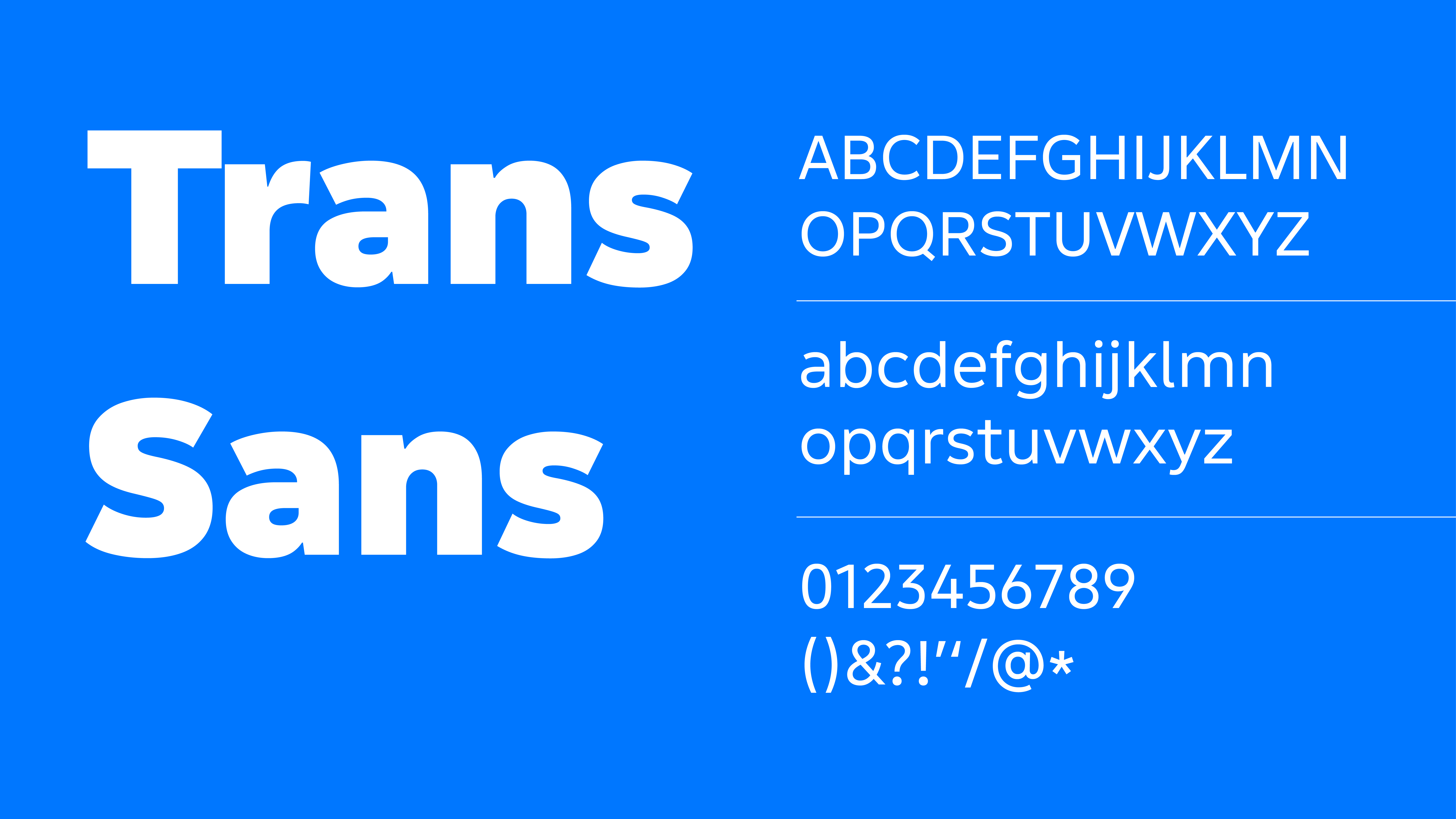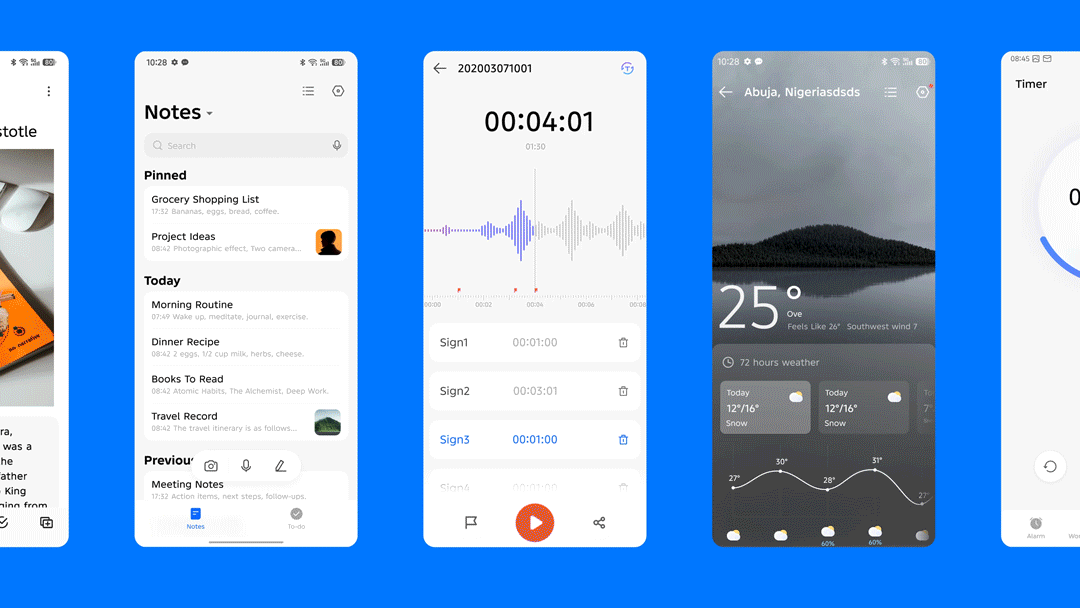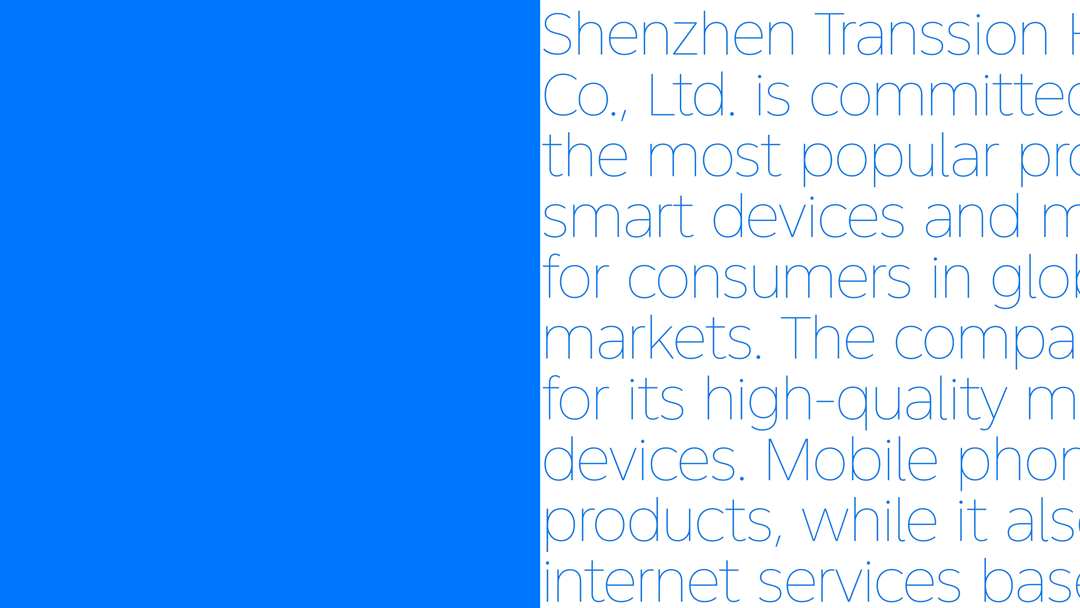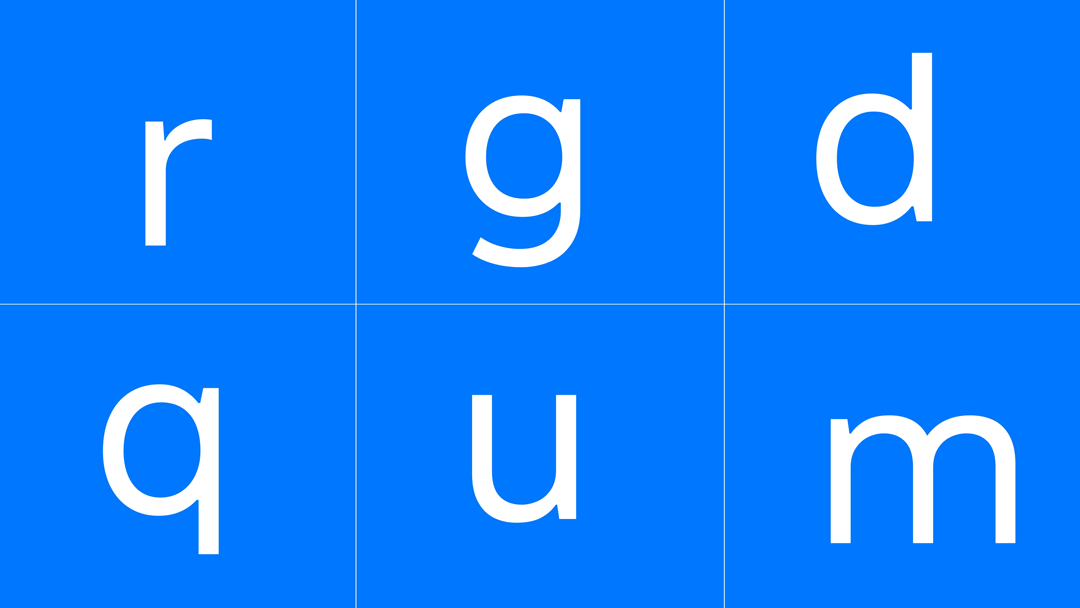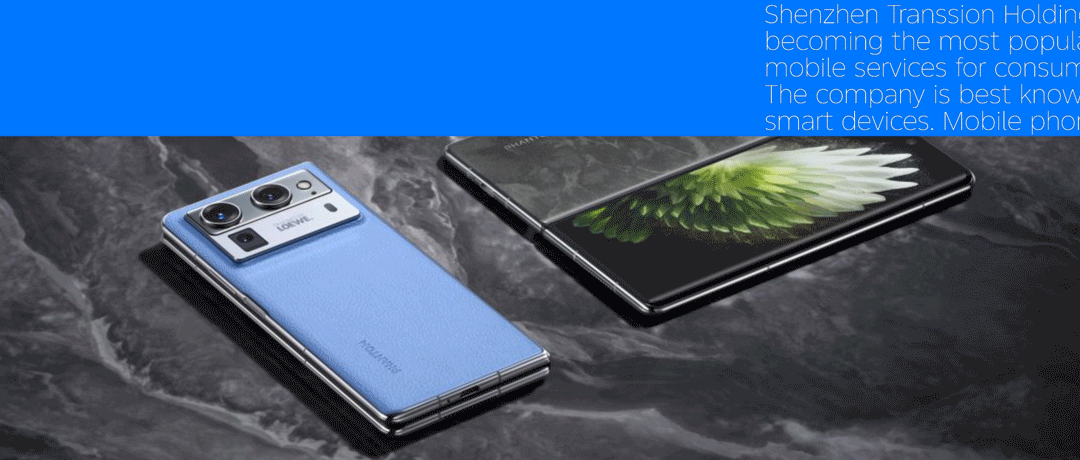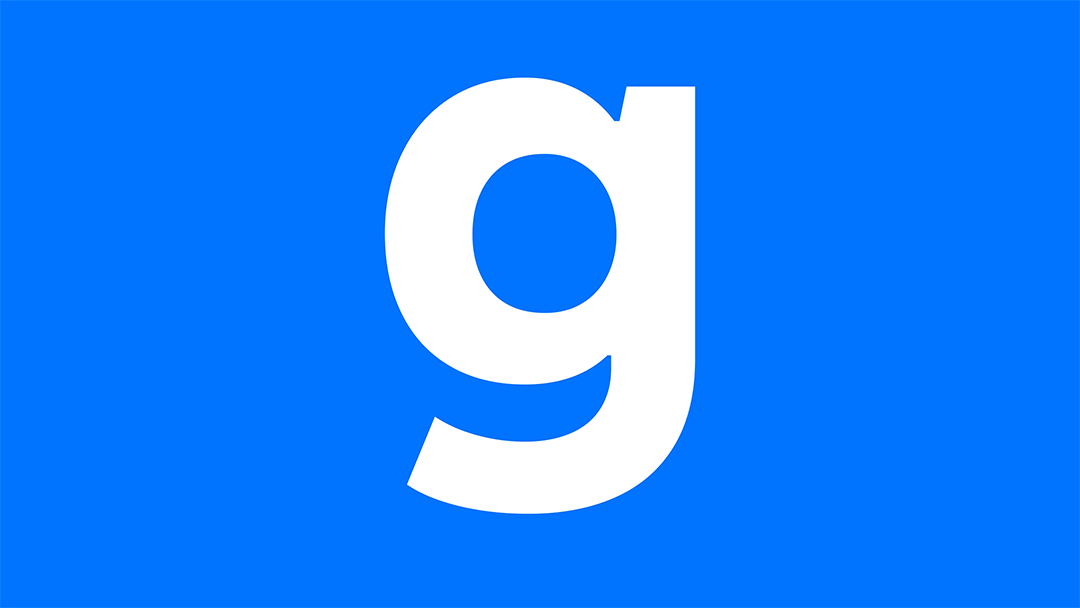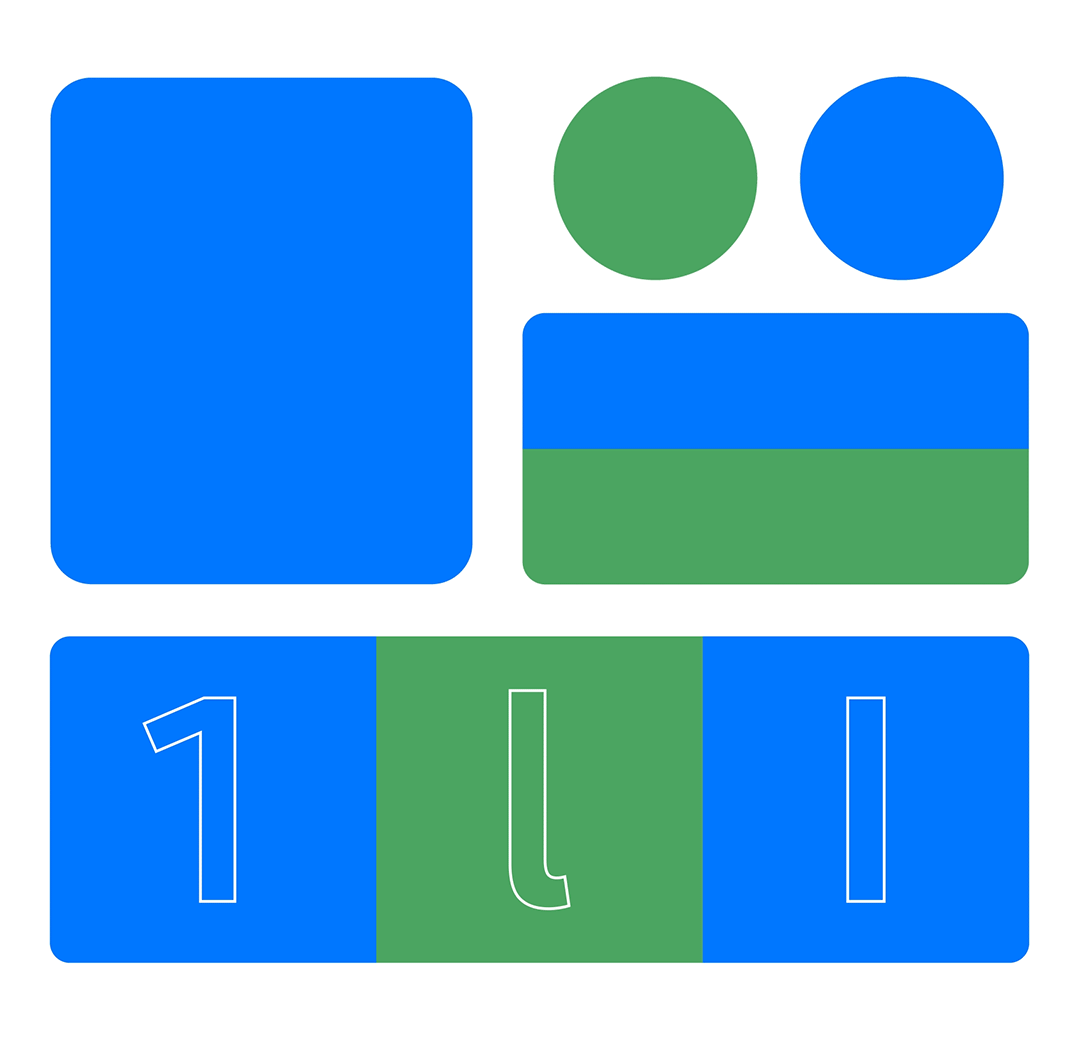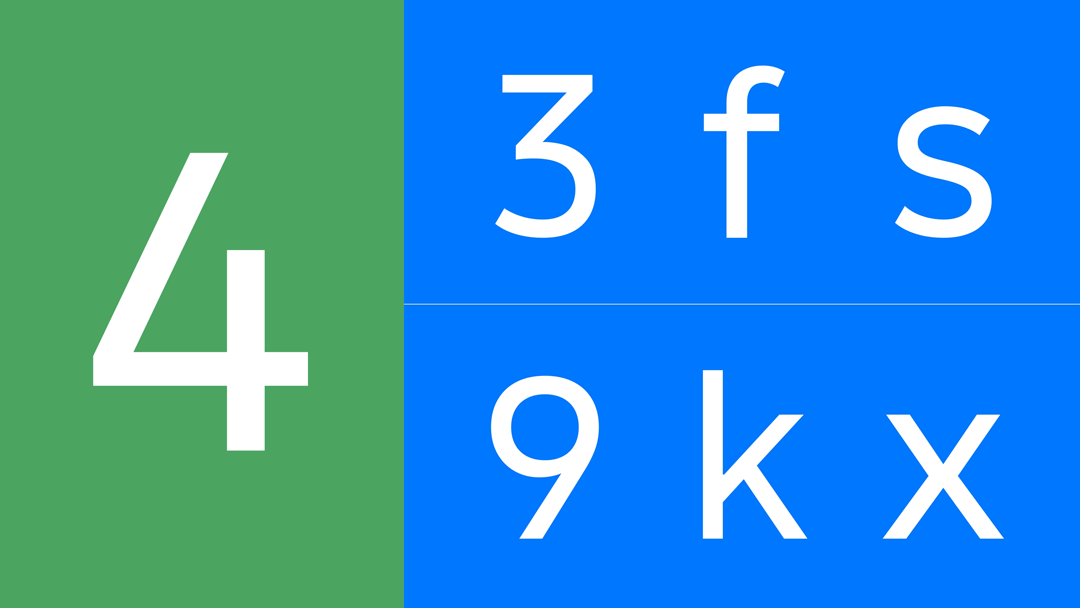
传音定制字体 TransSans:在多元语境中实现视觉与品牌的进化
作为新兴市场领先的智能终端设备和移动互联服务提供商,传音旗下拥有 TECNO、itel、Infinix 等知名手机品牌,并自主研发了智能终端操作系统传音 OS(包含 HiOS、itelOs 和 XOS),打造了“手机+移动互联网服务+家电、数码配件”的多元商业生态。
传音始终以新兴市场的消费者为中心,不断洞察和满足新兴市场人民的需求。随着全球业务持续扩展,传音意识到,智能终端产品的系统字体不仅承载着产品的视觉质感,也直接影响着不同语言用户的阅读体验与情感连接。
基于此,蒙纳字库(Monotype)为传音旗下三大手机操作系统 HiOS、itelOs 和 XOS 打造定制字体 TransSans,兼顾技术性能、视觉美感与全球本地化需求,助力传音强化品牌辨识度和用户体验一致性。
1 字体的品牌温度:差异化与“无界文本体验”
字体不仅是信息的载体,更是品牌精神和用户体验的重要组成。
基于传音全球化发展的需求,蒙纳字库打造的新字体在多语言、多文字体系下为不同使用场景带来更清晰、舒适的阅读体验,稳定适配不同字号和分辨率。
此外,新字体兼具传音旗下手机品牌 TECNO“现代科技”和 lnfinix“年轻、潮酷”的品牌气质,同时融合itel 的“ 可靠、亲和”,整体风格稳健且不失区分度。
通过字体的系统性升级,传音进一步提升了界面的视觉品质和品牌的统一性,为全球用户带来更为一致、更加温和的交互感受。
2 理性与人文,自信与高效
经过细致打磨,字体方案正式落地,并被命名为TransSans。字体包含从极细(Ultra Light)到加粗(Heavy)9 款字重,以及可变字体。
TransSans 整体为现代无衬线体风格,结构中正比例协调,笔画衔接自然、开口宽阔,极大地强化了可读性与识别性,尤其适配于移动终端多语言、多场景下的信息展示需求。
不同字重之间的对比度控制得宜,粗体字重醒目有力,常规字重则平衡亲和与现代,便于主次信息间形成视觉引导。
其次,TransSans 融入了几何元素与细微圆角,使其在科技感与人文亲和之间取得平衡。
此外,较高的 x 行高、适中的字宽与字间距设计,有利于提升小字号场景(如状态栏、桌面组件)下的表现力;数字和标点的风格保持统一,编排易于识别,适应天气大数字、倒计时等特定 U模块;字形端部的微圆角和略带活力的弹性,赋予字体年轻和动感特质。
TransSans 第一阶段聚焦于拉丁字符,无级字重变化,确保常用语言和系统场景的全量适配和上机优化;第二阶段,则扩展至更多语种,支持系统最大字符需求。 这是一款兼具极简理性与温和现代气质的通用无衬线体,精准、细腻、不喧哗,却始终透露着当代数字世界的自信与高效。
3 新字体上线:焕新的用户体验和品牌形象
无论是日常的桌面组件、信息流、任务列表,还是状态栏、天气大数字、笔记和多语混排等细分场景,用户通过新字体都能体验到更加舒适流畅的阅读感和主次分明的视觉层级。
多语言支持和小字号适配全面提升,赢得了传音团队和用户群体的积极反馈。
蒙纳中国区业务负责人王乾表示:“与传音的合作是一次极具创造力的体验。我们不仅用字体打破了美学与技术边界,也为传音构建了全球化、多语言兼容和差异化表达的视觉新基因。每个字符背后,都蕴藏着创新与包容的品牌精神,相信这种科技温度和美感会被越来越多用户感知。”
传音公司表示:“字体是我们用户体验升级中极重要的一环。蒙纳为我们带来了兼顾全球美学和本地体验的杰作。全新的系统字体助力传音智能终端产品焕发独特活力,让用户在系统的每一处细节都能感受到创新和品质的力量。这正是传音‘让尽可能多的人尽早享受科技和创新带来的美好生活’企业使命的印证。”
4 展望
作为全球数字字体与品牌视觉的推动者,蒙纳通过此次与传音的深度协作,不仅解决了实际工程与体验问题,更把可持续的高品质视觉语言带入新兴市场消费者的日常生活。
这一次,我们见证的不只是一个“系统字体项目”,更是技术与品牌温度、国际性与本地化、理性与感性共生的杰作。https://cn.monotype-asia.com/resources/article/transsans-case-study